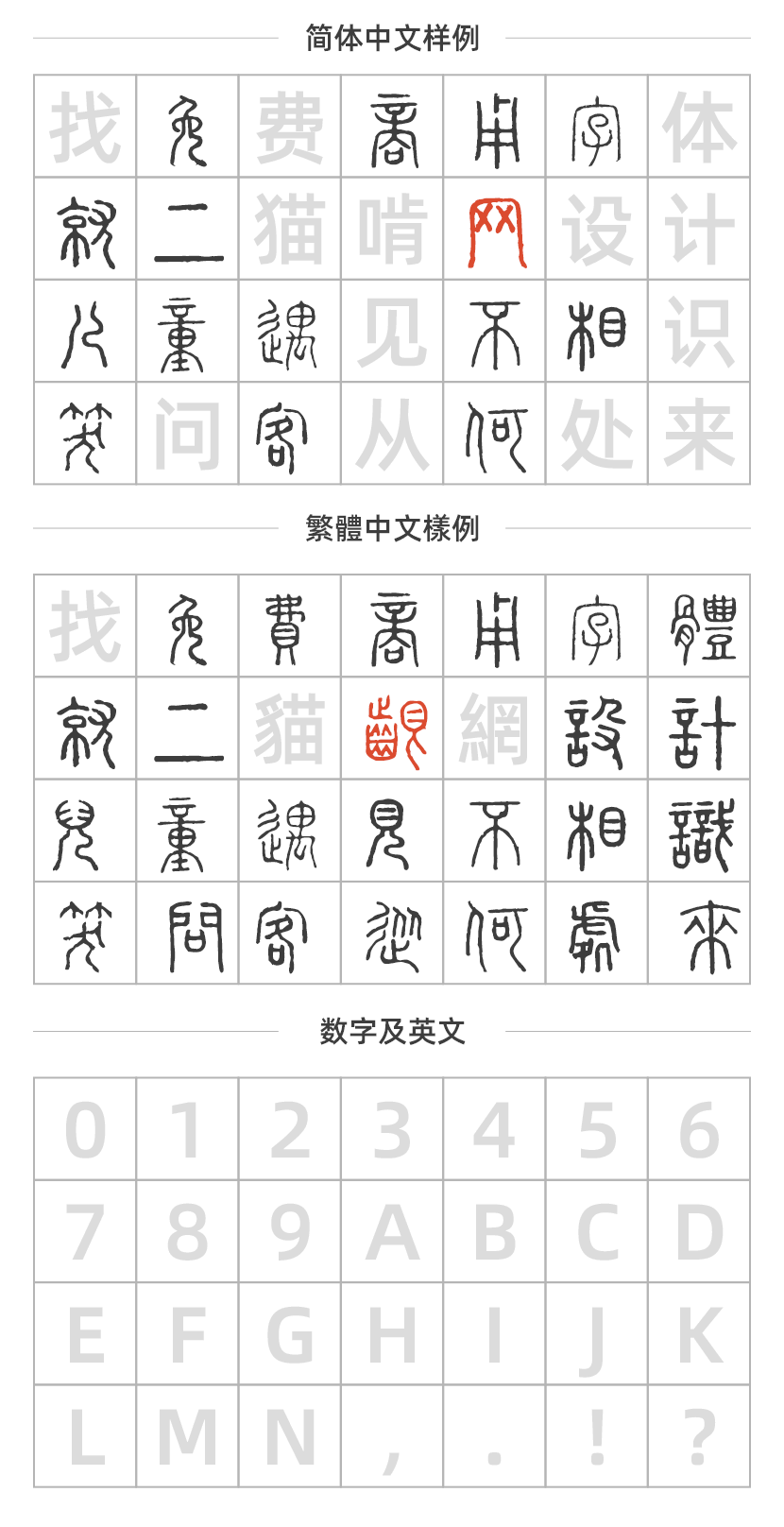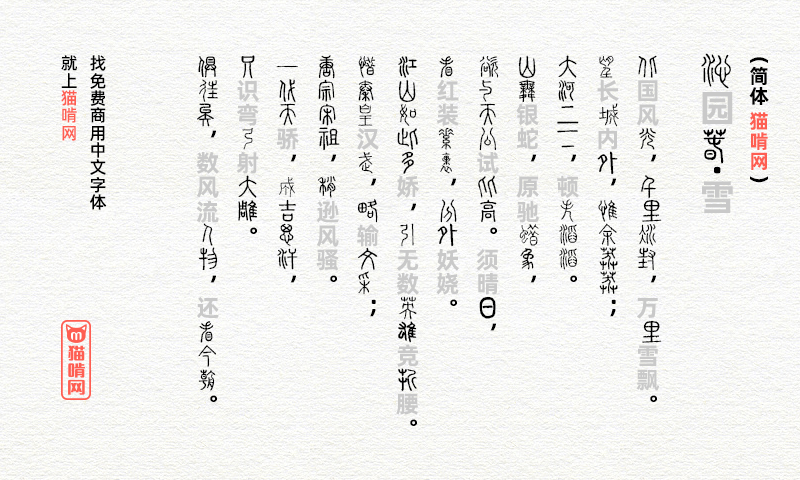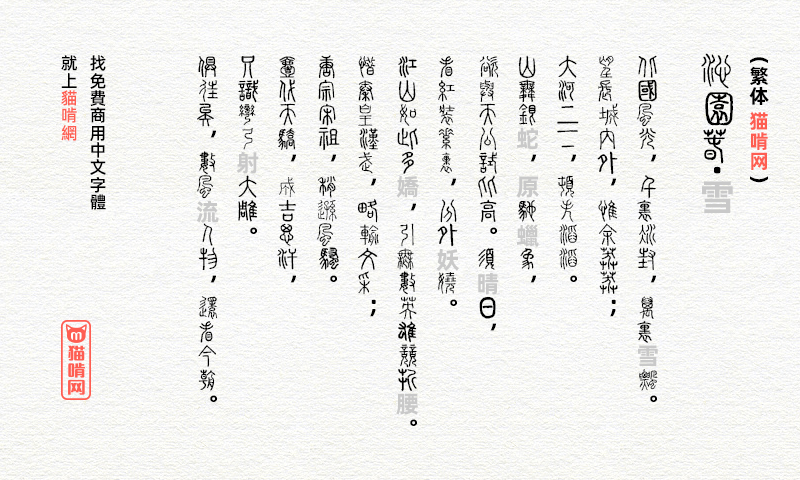
全字库说文解字:古色古香的小篆体字体免费商用
字体作者:全字库 (中国台湾) 字体字重:1个
中国文字发源及早,历经时代变革而长兴不衰,经历了甲骨文、今文、小篆、隶书、楷书、行书、草书等过程。而在中华五千年历史中,有一种文字承载物、像、形之美,展现汉字文化最纯粹的美,它就是小篆。
全字库说文解字是一款特别的中文字体,该字体采用小篆的风格。
《说文解字》是中国第一部系统地分析汉字字形和考究字源的字书,许慎著,成于安帝建光元年(121年)。原书十四篇,叙目一篇,正文以小篆为主,收9353字,又古文等异体同文1163字,解释十三万余字。
目前采用的版本为艺文印书馆所出版之《说文解字注》,后由南唐徐铉所校定,清代段王裁注之版本(世称大徐本)并参考黎明文化事业公司之《说文解字注》,及南唐徐铉所撰之《说文解字繁传》
由于说文解字原文与现行之Unicode编码并无一完整的对应,因此无法将所有的字形收录于本字体内。以致于会有部分字码无法显示出正确的字形!目前收录于本字体内的字数共6721个字。以 “全字库” 冠名的字体由中国台湾地区的行政机关开发并维护,其官网为 http://www.cns11643.gov.tw/